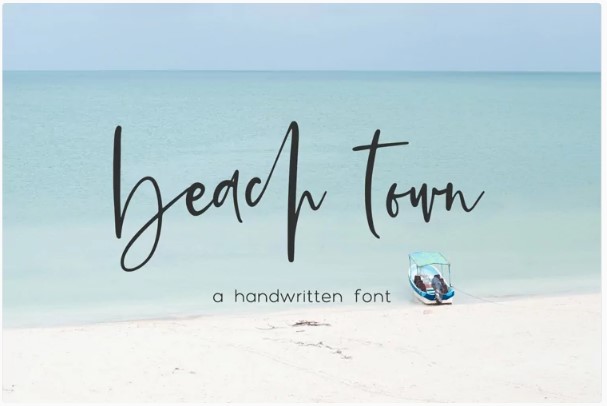
Представляем вашему вниманию Beach Town Script, рукописный шрифт в фирменном стиле.
Этот шикарный, стильный шрифт имеет небрежный, непринужденный вид, имитирующий почерк.
Beach Town Script лучше всего подходит для:
- логотипы + брендинг
- дизайн сайта + акценты на сайте - подумайте о дизайнерских блогах, блогах о путешествиях, блогах о моде и многом другом
- чистый печатный дизайн, например, журналы и флаеры
- элементы заголовков, которые требуют рукописного штриха
- графика цитат для социальных сетей
Beach Town включает в себя:
- все символы верхнего и нижнего регистра
- цифры + пунктуация
- 26 альтернативных символов нижнего регистра
- 36 лигатур: am an ar at bb bl cc ch ck cl dd dd ee er ff fi fl fo gg ll mm nn of ol oo or ph pl pp rr sh ss st th tr tt ur
- Поддержка западноевропейских языков